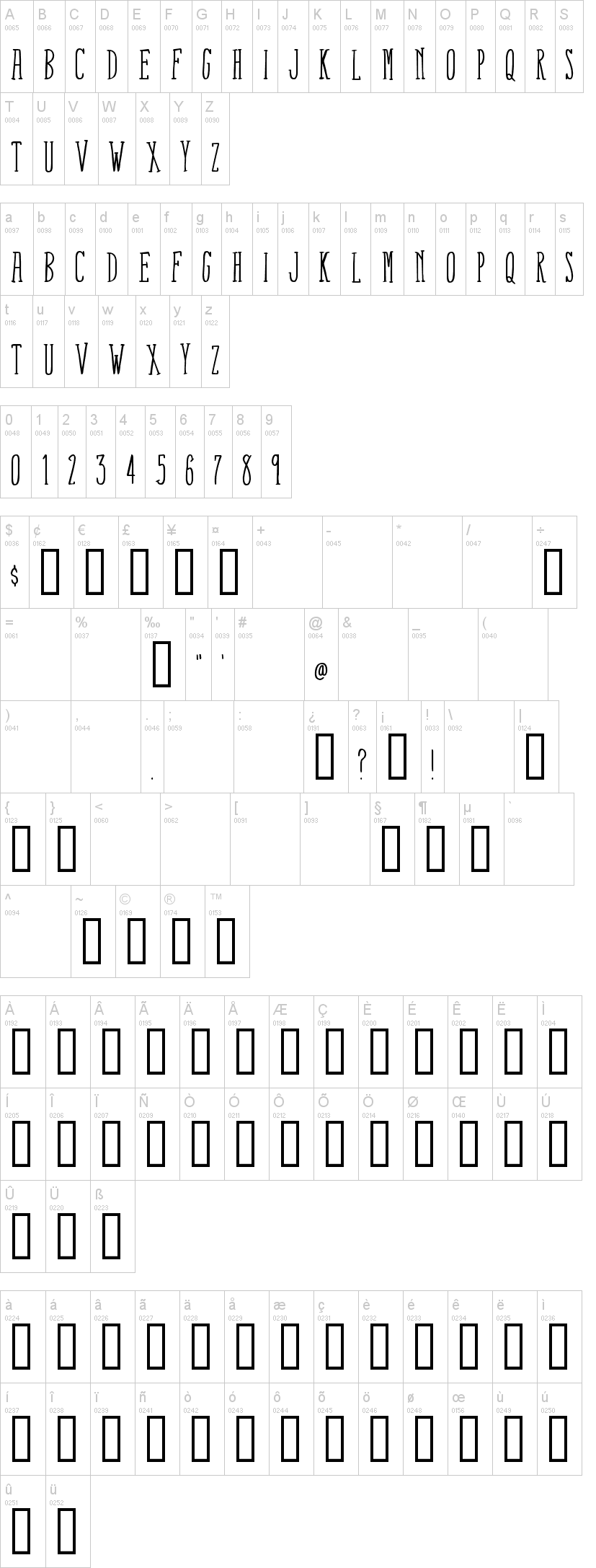
Fox Connection
Fox Connection是一款由英国设计师João Miranda创作的手写字体,其设计灵感来自于手写草书字体的风格。这款字体的特点是其线条流畅、简洁、有趣,给人一种轻松愉快的感觉。 Fox Connection有两种风格:一种是普通字体,另一种是手写字体。普通字体的线条较为规整,整齐划一,适合用于正式的商务场合;手写字体则更具有个性和艺术性,适合用于儿童书籍、广告宣传等场合。 Fox Connection字体具有良好的可读性和清晰度,不论在小字体还是大字体下,都能保持清晰的显示效果。同时,它还支持多种语言,适用于不同国家和地区的文字排版需求。 总体来说,Fox Connection字体是一款非常优秀的手写字体,具有良好的设计风格和实用性,适合用于各种场合的文字排版。
Fox Connection是一款非常不错的手写艺术字体,具有很好的视觉感,适合于文化类的宣传设计、商业类品牌的广告和产品包装设计以及个性化文字排版等较多场景。
Fox Connection字符映射图